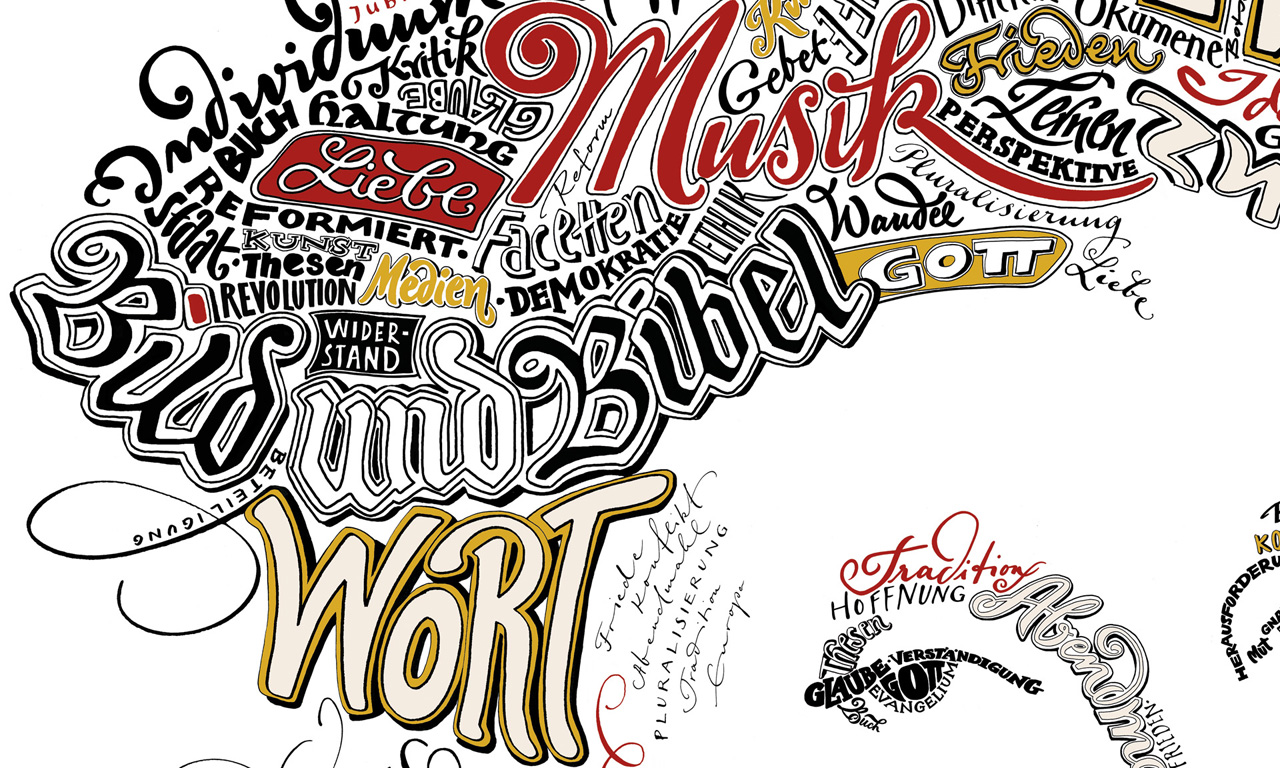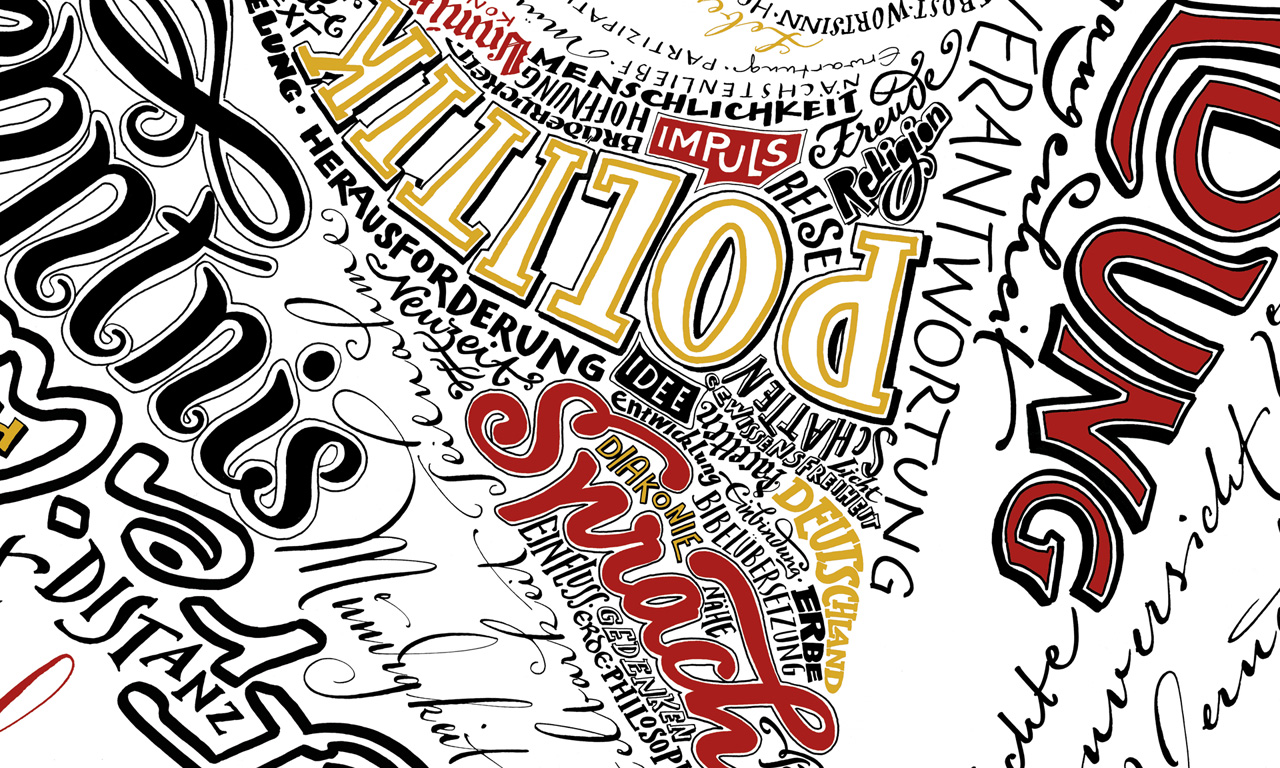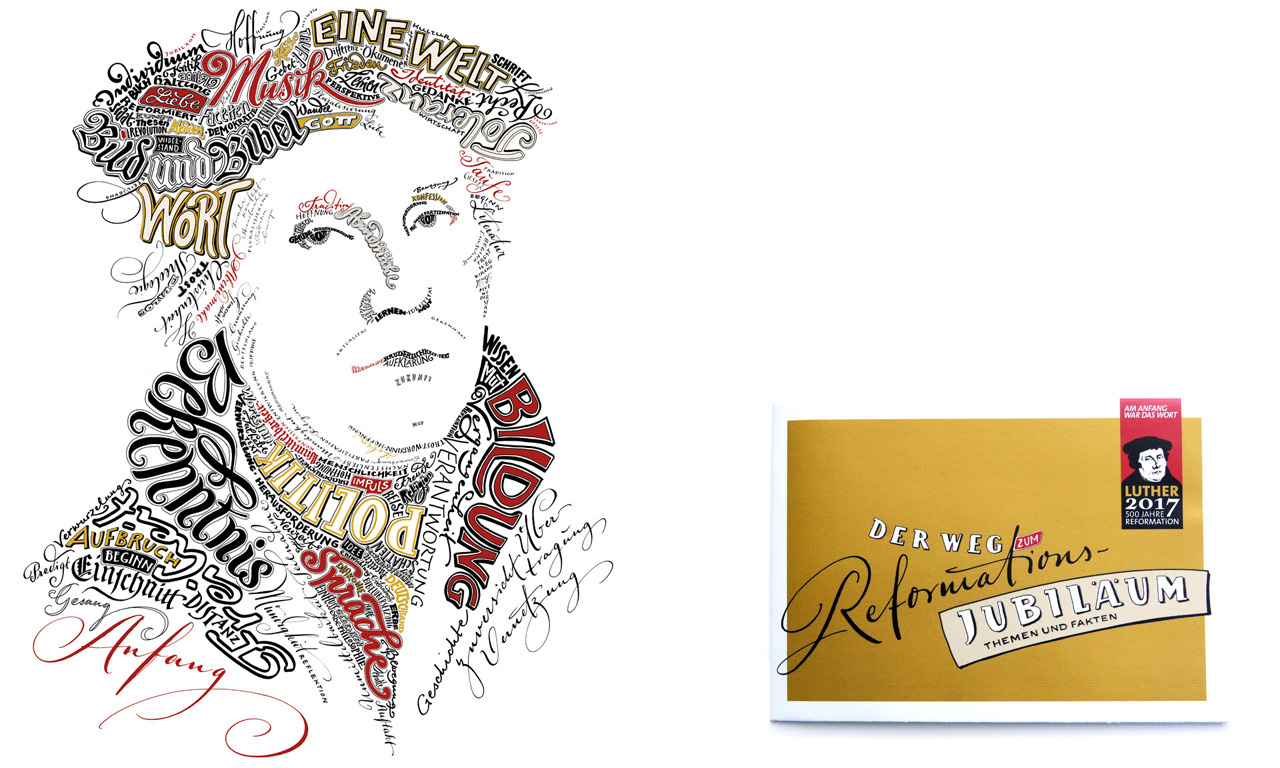
Luther-Portrait
Collage aus Kalligrafie, Handlettering, Brushlettering und Faux Calligraphy.
Da sich das kalligrafisch illustrierte Lutherportrait sehr schnell großen Beliebtheit erfreute, wurde ich im Rahmen des Kirchentages in Hamburg für ein Live-Lettering gebucht. Das Lutherportrait entstand auch hier aus Worten, jedoch »live«, auf einer 4,0 x 4,0 m großen Leinwand. Ein Teil der Worte waren Bestandteil des Briefings. Ein Großteil der Worte kamen jedoch direkt aus dem Publikum und wurden spontan von mir auf die Leinwand gebracht, ohne vorherige Entwürfe oder Vorzeichnungen.